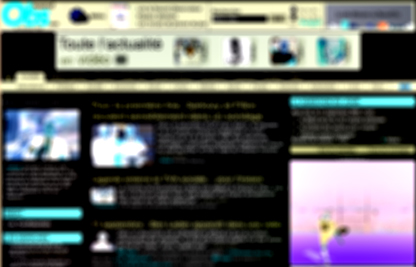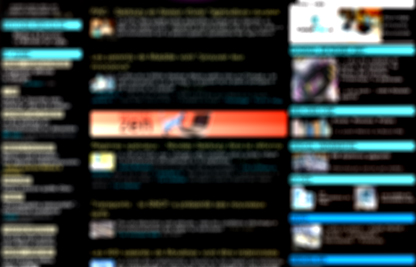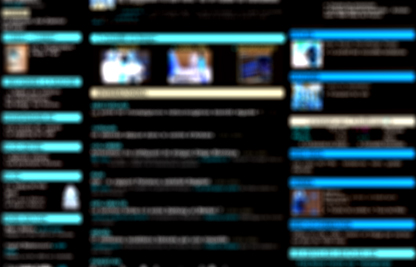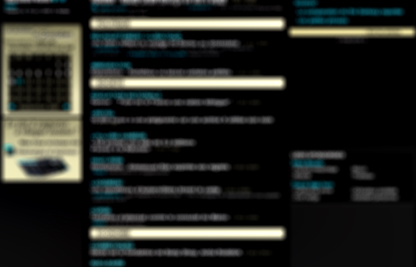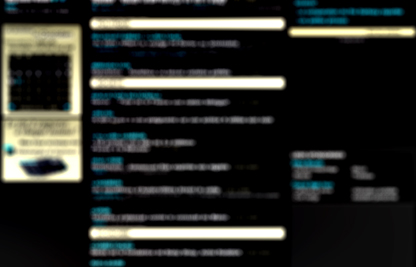
Radiographié le site du NouvelObs | décryptage
Découvert le nouveau site du NouvelObs relooké par Nata Rampazzo et je l’ai passé dans mon appareil à radiographier les sites web :-).
Où il apparait que la home peut-être divisé verticalement en 5 pages de scrolling (sur un écran 1600×1200). La première ci-dessus ne semble pas poser beaucoup de problèmes, mise à part le bandeau supérieur qui, avec le cartouche central (toute l’actualité en vidéo) avec ses minicartouches carrés semble franchement posé là comme un cheveu sur la soupe. Son positionnement centré ainsi que l’espace laissé au-dessus et en-dessous me semble ne pas correspondre à la rigueur graphique auquel Rampazzo nous avait habitué. Bien entendu il fallait laisser l’espace pour permettre aux onglets d’exister, mais l’approximation graphique de cet espace ainsi que le trou de chaque côté du cartouche central me semble un peu gênants.
C’est d’autant plus dommage que le cartouche se transforme en bandeau publicitaire après quelques temps et trône d’un coup au milieu de notre champ visuel de manière assez violente. Le NouveObs devra sélectionner ses pubs avec à propos, c’est certain. Le modèle économique de ce portail d’actus est entièrement basé sur la pub. D’où un vrai problème de stratégie graphique pour garder l’identité «du journal» sans tomber dans une vision surcoufienne des pages web. À se demander s’ils ne devraient pas proposer une version payante qui serait allégée d’une partie de la pub et donnerait à lire et voir un journal un peu plus proche des convictions des lecteurs —même si, et peut-être parce que, ces lecteurs sont aujourd’hui des CSP++ et pourraîent être tentés de s’enfuir d’un tel univers «au rabais».
Les vrais problèmes apparaissent en scrollant vers la deuxième page ici ci-dessus, et la troisième ci-dessous.
En effet ce que révèle cette radiographie (qui n’est pas un vrai eye tracking mais juste une méthode pour se dégager des signifiés et nous laisser apprécier la trame graphique) c’est que notre regard est véritablement agressé par ces filets horizontaux au détriment du contenu sémantique. Il y a là un vrai danger de fatigabilité pour l’utilisateur.
Les deux dernières pages de scrolling, le jeu se calme pour revenir à un équilibre des signifiants-signifiés.
Ce test est une méthode que j’ai repris des planches d’études d’eye tracking fourni par certains appareils d’analyse. Il n’indique absolument pas le déplacement et les points de fixation de nos rétines… Cependant il révèle la structure graphique sur laquelle un appareil de test va positionner ces points de fixation. En ce sens il devient évident qu’il ne remplace absolument pas un test utilisateur en grandeur réelle… Reste à voir si de tels tests ont été menés et dans quelles conditions.
Et juste pour terminer ce mini analyse, la typographie, même si je n’aime pas les guillemets verticaux :-) semble plutôt bien travaillé, à ceci près qu’il me semble qu’on se fatigera assez vite d’un Arial sur fond blanc-écran qui perce littéralement nos rétines sans aucun confort.
Bel exercice Peter. Méthode très viable et très pédagogique.
Je m’attendais à beaucoup mieux de la part de Rampazzo. En plus d’être difficilement lisible et plein de pub, ce site est lassant.
Alors pourquoi est-il lassant ? A mon avis, ça vient d’une absence totale de respiration, de bandeaux rubriques sans finesses, de choix couleurs fatiguants. Ca vient aussi de l’empillement à la suite façon totalement lourdaud. Et la tête de page avec son bandeau publicitaire qui flotte. la lisibilité est tuée par l’emploi de taille de caractères typographiques mal réglés. Un effet de cascade dans les tailles qui est très fatiguant d’autant qu’il n’y a pas assez de contenu pour apprécier le gris typographique. L’oeil ne fait que zapper sans stopper nul part. Il est impossible de se concentrer sur le coeur de page tant l’oeil zap à droite et à gauche.
A croire que Rampazzo est meilleur pour l’édition que pour les site internet ce qui est surprenant de la part de spécialistes de la lecture.
Il est bon de noter que ces remarques pour la plupart peuvent aussi s’appliquer au site de Libération dont la home est tout aussi fatigante, le code couleur en moins et c’est déjà ça.
Verdict : un site internet à refaire et à repenser de fond en comble tout comme la maquette du magazine d’ailleurs, mais ceci est un autre sujet.